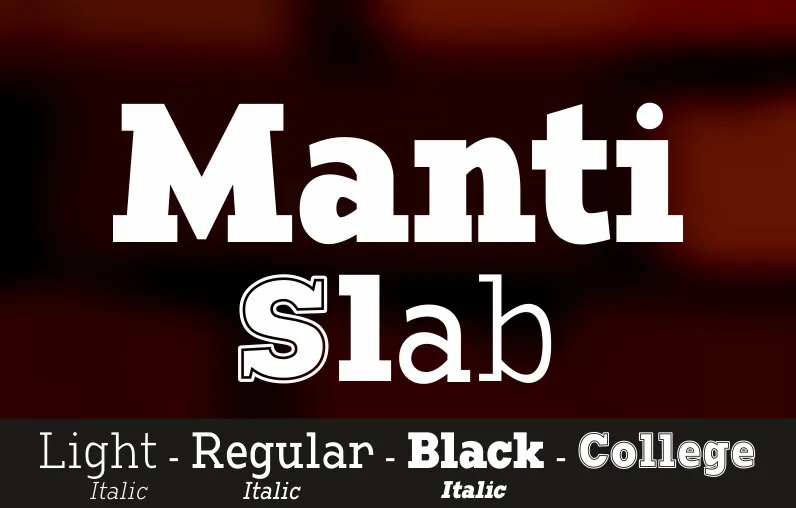
Aqui está uma descrição em português do Brasil para a página de download da font ‘Manti Slab Font Family’, mantendo-se fiel à descrição original e seguindo as instruções: Introduzimos Manti Slab, uma família de tipo de serif que se destaca por sua aparência suave. O estilo retro e condensado faz deste um bom escolha para projetos de marca. Ideal para aplicativos em tela e design editorial, essa fonte atende a diversos tipos de projeto gráfico. Manti Slab é projetada para ser usada em todo o espectro do design, desde embalagens até textos longos em layouts editoriais. Suas características humanizadas e a boa contrastes entre os traços finos e grossos garantem legibilidade notável, mesmo em grandes fóruns de texto. Para aumentar ainda mais sua versatilidade, o conjunto alternativo de gílias incluído ajuda a dar um toque único e diferente aos seus projetos. Com Manti Slab, você encontrará uma opção criativa para seu próximo projeto, sejam eles em tela ou offline. A fonte é particularmente útil em aplicações multimedias como aplicativos móveis e materiais impressos, e também ideal para criação de identidade visual. Experimente-o agora!